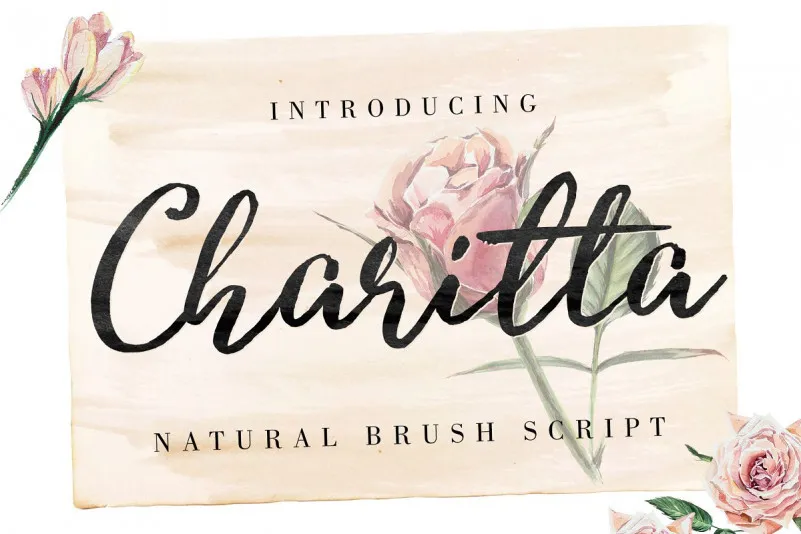
Charitta Organic Script Font – Download Grátis
Aqui está a descrição que você solicitou: Esta nova fonte Brush, criada por Lettersiro, é uma variedade chamada Charitta Brush Font e também pode ser encontrada como uma fonte Script denominada Charitta Organic Script Font. Esta é uma fonte orgânica feita com a ajuda de um canivete-pen, característica que oferece um visual natural e autêntico à sua tipografia. Ideal para logotipos, mensagens inspiradoras ou rótulos de produtos, esta fonte vem tanto em minúsculas quanto em alternativas maiúsculas. Ela permite que você crie textura única e incrivelmente detalhada em apenas alguns cliques. Aventure-se no universo dos materiais de propaganda e publicidade com essa fonte de estilo Script. Perfeita para slogans impactantes, rótulos atractivos ou até mesmo na criação de conteúdo gráfico personalizado para moda e vestuário. Esta font oferece o poder de ser utilizada tanto em trabalhos profissionais quanto em designs artísticos pessoais, fornecendo uma opção versátil que se adapta a vários contextos. Aproveite-a agora para dar vida à sua ideia com estilo.